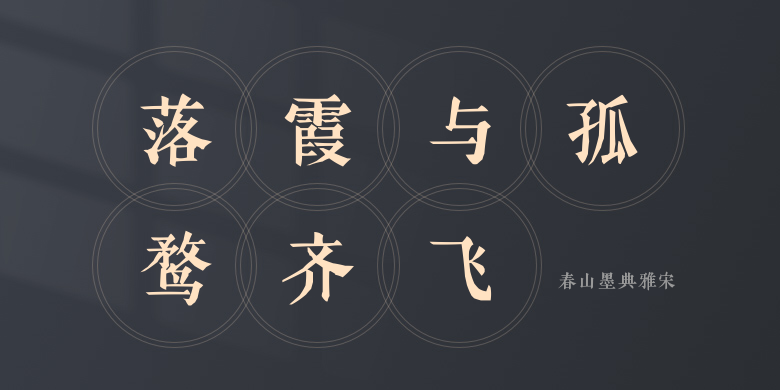
春山墨典雅宋
春山墨典雅宋,这款字体结构工整、笔画清晰,兼顾美观与易读性,适用于标题、正文、海报、包装、LOGO 等多种场景。字形优雅稳定,风格百搭耐看,适配日常排版与创意设计,让文字呈现更舒适、更具质感。春山墨典雅宋一笔一画,皆是细节,以均衡的比例、流畅的线条打造舒适视觉体验,字形端正大气,风格简约现代。无论是商业设计、品牌宣传还是日常排版,都能轻松驾驭,让文字更有格调与力量。春山墨典雅宋字体下载。